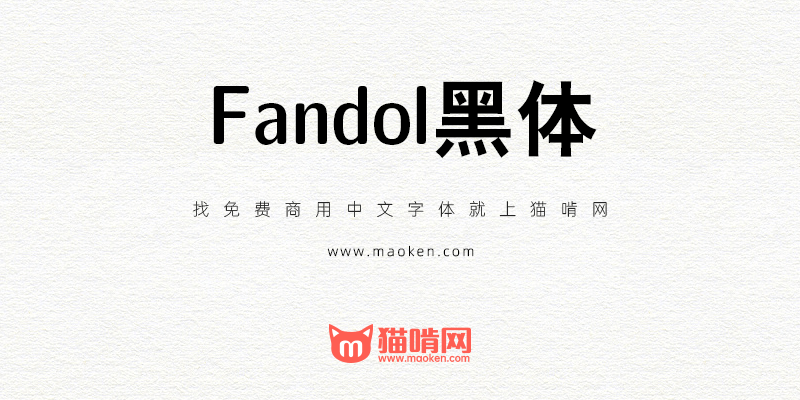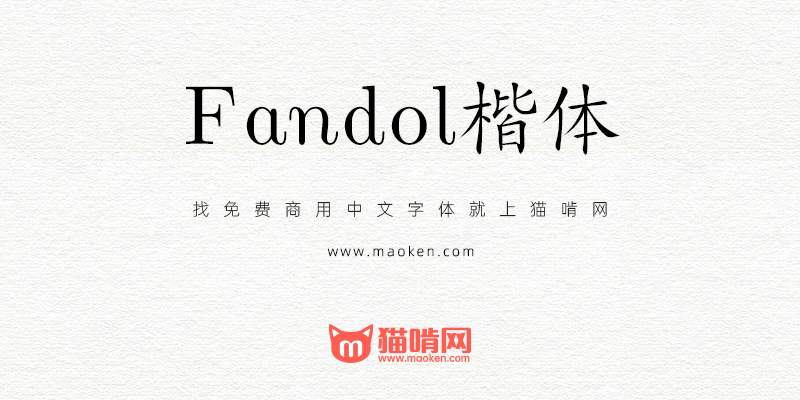
Fandol字体:四套来自破产公司的字体 字体授权存疑 不建议商用
Fandol字体专为中文排版而设计。目前的版本包含四种风格:Song,Hei,Kai,Fang,所有字体均为OpenType格式。
对于Fandol字体版权,网上的免费字体文章中都介绍为可以免费商用。但是有读者向猫啃网提出,这款字体能否免费商用现在并不确定。而在知乎上也有人提出说,Fandol字体是不能免费商用的,而且Fandol的字体制作者也在知乎上。
关于这个授权的出处,站长之前也已经有看到过。但是对于这款字体,在知乎上颇具争议。关于争议这款字体的帖子在这里:https://zhuanlan.zhihu.com/p/49112433,而猫啃网有再次询问发贴的这位网友,得到的回复也是不能商用。
为此,猫啃网也联系在知乎上联系到了Fandol字体的作者,得到的回复也证实Fandol字体不能免费商用,因为这款破产字体充满了争议,所以猫啃网还是建议不要使用这款字体。建议大家可以使用方正的四款字体进行代替。方正黑体方正仿宋方正楷体方正书宋
Fandol黑体
Fandol楷体
Fandol宋体
Fandol仿宋
所以,要警惕这类冒充可商用授权协议的字体。
尽管只能在LaTeX上使用,也不能排除未经字体版权方书面授权(废氪金)擅自使用的侵权行为(也就是赔偿,但我不确定赔偿不起的时候,会不会上征信)。
• 实际上LaTeX上使用也是有被汉仪起诉的风险,实际上整个字形都是照搬的汉仪。。。。可以说是非常糟糕的行为。。。。
• 如果是照搬汉仪字体的话,那这些字体就是盗版字体!因此我已经说过了,GPL授权协议对这款字体就是伪造的!
• 所以,千万别上了Fandol字体授权协议的当!
• 换句话说,正常用途就应该从汉仪那里买对应字体的对应授权才对……(主要是中文部分)
所以,“GPL加可嵌入文档的字体例外”授权协议是陷阱,不可信!尽管这些字体只能用于LaTeX。
• 授权协议不是陷阱,有问题的是这个Fandol字体的作者,完全照搬的汉仪,我今天对比了Fandol的仿宋和汉仪仿宋简,很遗憾两个字体可以说毫无区别,接近100%的相似率
• 对,因为是照搬汉仪的,所以它已经侵权了;所以对这款字体来说,授权协议……就是陷阱。
那 GPL 协议估计就是冒充的。
根据作者的说法,Fandol的中文字体,部分是通过扫描金属活字trace成外框然后用FontForge调整细节得来的:
• 这个扫描金属活字是俄风数学字体(a set of Russian style math font),中文字体目前来看黑体和宋体与汉仪脱不了关系,使用风险很大。
• 可以说该字体涉嫌版权侵权?
fandol系列被称作“破产黑体”,以及是破产公司做出来的,这些都是网上广为流传的谣言,请不要再以讹传讹了。
• “破产”据说是直接机翻“Fandol”得到的…
• 这份出处我之前已经看到过了,只是在知乎上有一位貌似是所作者的朋友在争议这个事情,再加上后来我在知乎上直接向原作者求证了,所以这款字体我还是归类于版权存疑问,不建议商用。
你好,既然這個字體不能商用,要不要把標題和封面改一下?
究極亞米緹Official6年前 (2020-05-27)回复
• 好的,我稍后改一下。
猫啃网6年前 (2020-05-27)回复
11. #0
刚刚又“格物致知”了一下。GitHub 与 CTAN 上的 Clerk Ma 应该就是马起园;而在 LuaTeX-ja 的 OSDN 发出 commit (dc8b1c16a51c0f53e28af21fed59db870d8265c7) 删掉 luatexja-zhfonts 的 MaQiYuan 自然也应该是马起园;OSDN 的 MaQiYuan 与知乎上的李阿玲头像又是一致的。所以,我有把握猜测,马起园、Clerk Ma、MaQiYuan、李阿玲可能是同一人。奇怪的是,他(她?)在 CTAN 上上传 fandol 包时,用的明明是 GPL + GPL font exception(不仅可以商“用”,而且可以“改”,只要遵循 GPL),私信中又说不可免费商用……好迷。
AgCl6年前 (2020-05-03)回复
• 这个我也比较蒙~~既然存在不确定性,还是把这款字体列为不可商用的。毕竟这几个字体还是有很多能替换的
猫啃网6年前 (2020-05-03)回复
• 我认为原因是这套字体跟汉仪有关系,所以他说不能商用。你能不能拿那张对比图问一下 CTAN 的人,里面的包 Fandol 是不是涉嫌侵犯版权?
Euarne4年前 (2022-08-27)回复
• 马起园与李阿玲确实为同一人:https://tuna.moe/blog/2015/tex/
沫鸦9个月前 (11-05)回复
12. #0
您好,刚刚看到这个网站,感觉很良心!我想说的是,至于 Fandol 字体,其作者应该是马起园、苏杰等人,使用 GPL + GPL font exception 协议(详见 https://ctan.org/pkg/fandol)。LaTeX 的 CTeX 宏集手册(http://mirrors.ctan.org/language/chinese/ctex/ctex.pdf)与 LuaTeX-ja 的一篇文档(luatexja-zhfonts.pdf,CTAN 上最新版本 LuaTeX-ja 已不存在)中也有提到。只不过作者貌似删库跑路了(https://github.com/clerkma/ptex-ng-dist/issues/5)……
AgCl6年前 (2020-05-02)回复
• 谢谢!
雲逸子6年前 (2020-06-06)回复
13. #0
可能是因为你说该字体是破产字体,她生气了,所以说不可以商用,哈哈哈哈
医学科研绘图6年前 (2020-04-03)回复
• 这个不是我说的,哈哈,是网上大家都这样说的~
猫啃网6年前 (2020-04-03)回复
• 哈哈哈哈,有可能。
雅图6年前 (2020-05-12)回复
14. #0
黑体、宋体、仿宋用的是汉仪的字体吧,楷体不清楚。
lxgw6年前 (2020-02-27)回复
• 应该不是汉仪的字体吧,据说字体的作者在知乎上有帐号,只是具体是哪个不知道,所以没法找他进行咨询。
猫啃网6年前 (2020-02-27)回复
• 你附的知乎链接(https://zhuanlan.zhihu.com/p/49112433)下方ManTingFang的评论回复里,点开里面有疑似作者【李阿玲】
sa3m6年前 (2020-02-28)回复
• 看他们的对话,那个李阿玲似乎不是作者本人
猫啃网6年前 (2020-02-28)回复
• 你需要点进他主页,翻看他历年的文章和动态,(如https://zhuanlan.zhihu.com/p/41809557)就会发现他的工作就是做LauTex相关的,然后因需要才做了字体,而且Fandol这个关键词多次出现等,综上他是相关者的可能性非常高,只是我当初排查的时候觉得即使他是,这个字体系列应该也不会免费商用,只是当初他公司的副产品,就不想费时间再往下调查了。
sa3m6年前 (2020-02-28)回复
• 看样子可能性十分高,我已私信问他具体的情况了,不过不知道他会不会回复我~~感谢你的查证,希望可以让设计师们少跳点坑~~
猫啃网6年前 (2020-02-28)回复
• 还有这条标题为【Fandol字体下一代字体计划】的https://zhuanlan.zhihu.com/p/22519738,都让我觉得他是制作者的可能性很高
sa3m6年前 (2020-02-28)回复
• 【Fandol字体更新】https://zhuanlan.zhihu.com/p/21288751
【Fandol字体更新:点阵风的矢量字体】https://zhuanlan.zhihu.com/p/21288751
【简讯:FandolFangSongScript字体】https://zhuanlan.zhihu.com/p/20734772
【Fandol字体更新:0.3版本,字体版本1.3】https://zhuanlan.zhihu.com/p/20118021
以上是之前考究时,找到的相关链接,还有很多我就没仔细找了
sa3m6年前 (2020-02-28)回复
• 可以把 Fandol 的字体跟汉仪字体进行对比,Fandol 粗黑跟汉仪大黑除了英文数字之外一模一样,Fandol 宋体(Regular)从“关”“春”“以”等字看出来,改的是汉仪书宋二S,就差英文数字了。
lxgw6年前 (2020-02-28)回复
15. #0
链接失效了
边吻贤殇7年前 (2020-02-22)回复
• 你好,下载链接已经修复了~~感谢你的指正
猫啃网7年前 (2020-02-22)回复
16. #0
长城字库算不算破产字体呢?好像找不到他们的字体业务了
NoviceHou7年前 (2019-10-25)回复